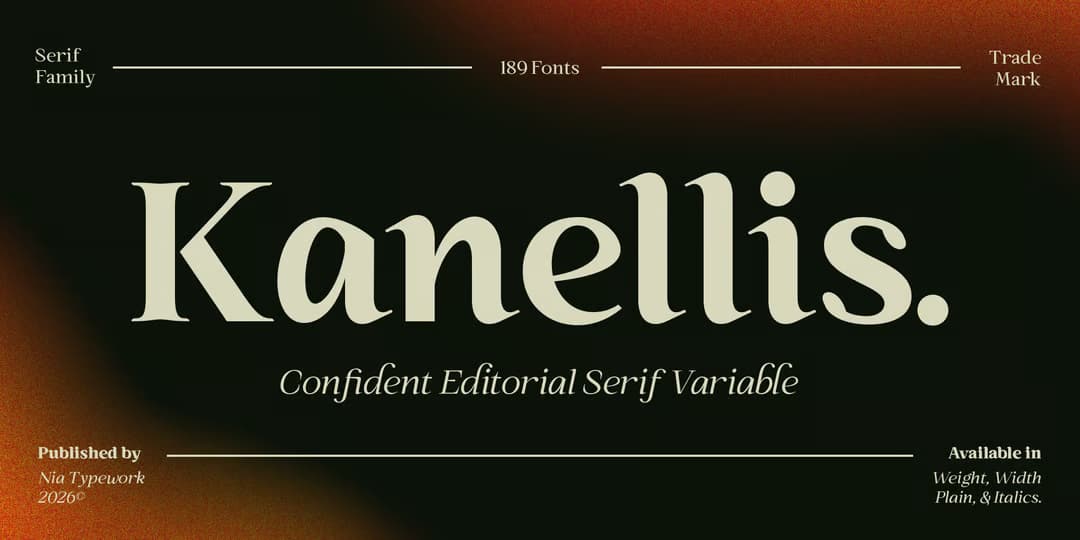
Kanellis
ちょっと変わったグリフを持つモダンローマン。セリフにやや凹みがあるクラシカルなスタイルのモダンローマンで、レギュラーの他、画像のように小文字がイタリックを垂直にしたグリフの Plain というファミリーを持っている。レギュラー、Plain、イタリックにそれぞれ字幅が Extra Condensed から Extra Expanded まで7種もあり、さらにそれぞれが9ウェイトあって、合計189種というかなりのビッグファミリーとなっている。その代わりと言ってはなんだが、あんまりグリフは多くない(笑)。バリアブルタイプもあり。元々がパックで $100 程度と破格の安さだが、ただいま30%オフセール中。